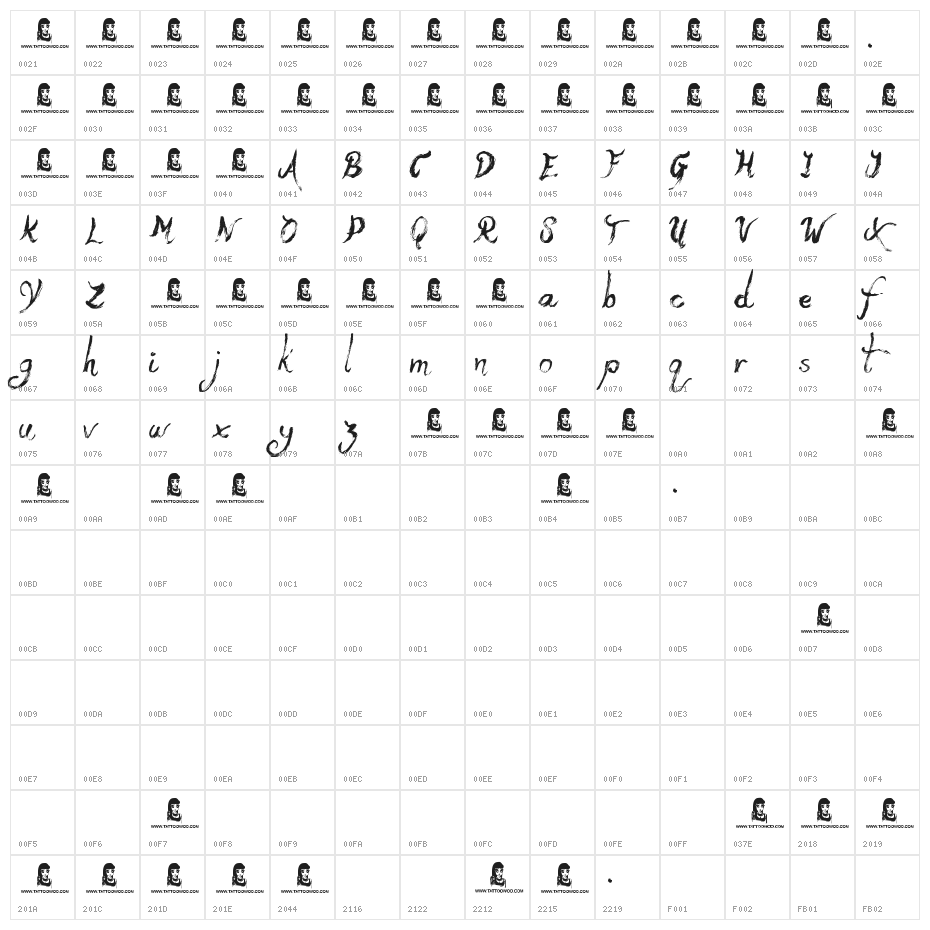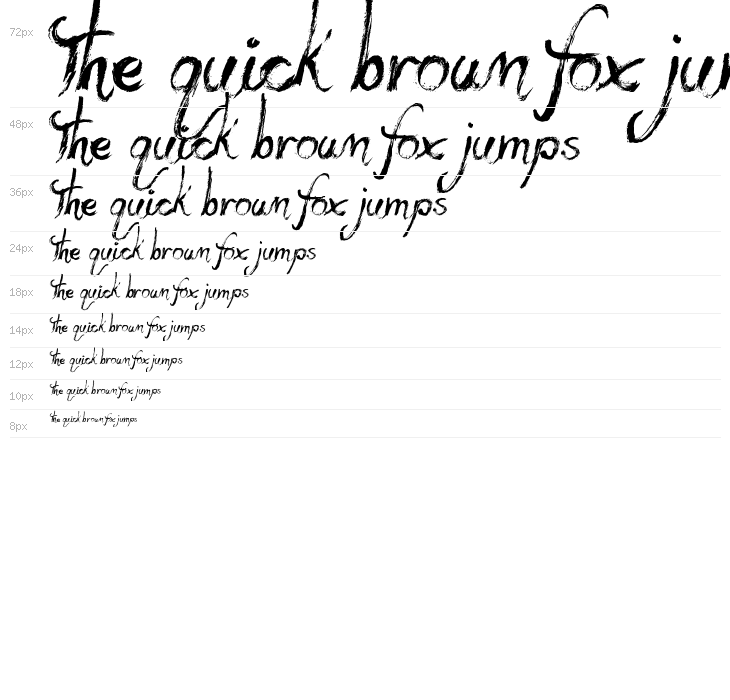
Yeti Fety Font
✎ Script
| 分类 | Script |
| 使用场景 | Logos, Headlines, Artistic projects |
| 推荐项目 | Ideal for branding, posters, album covers, and artistic projects that require a bold, personal touch. |